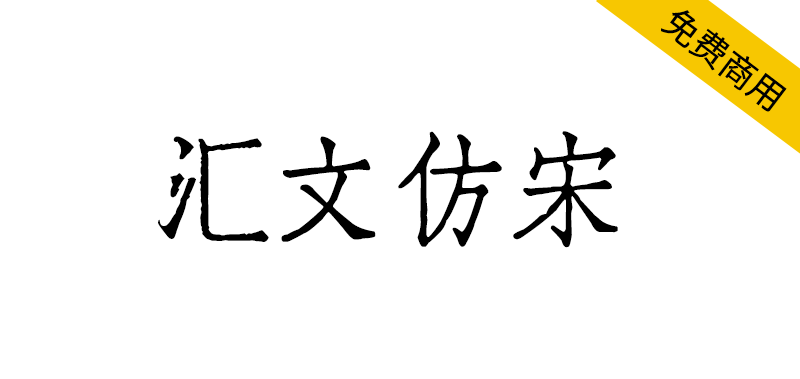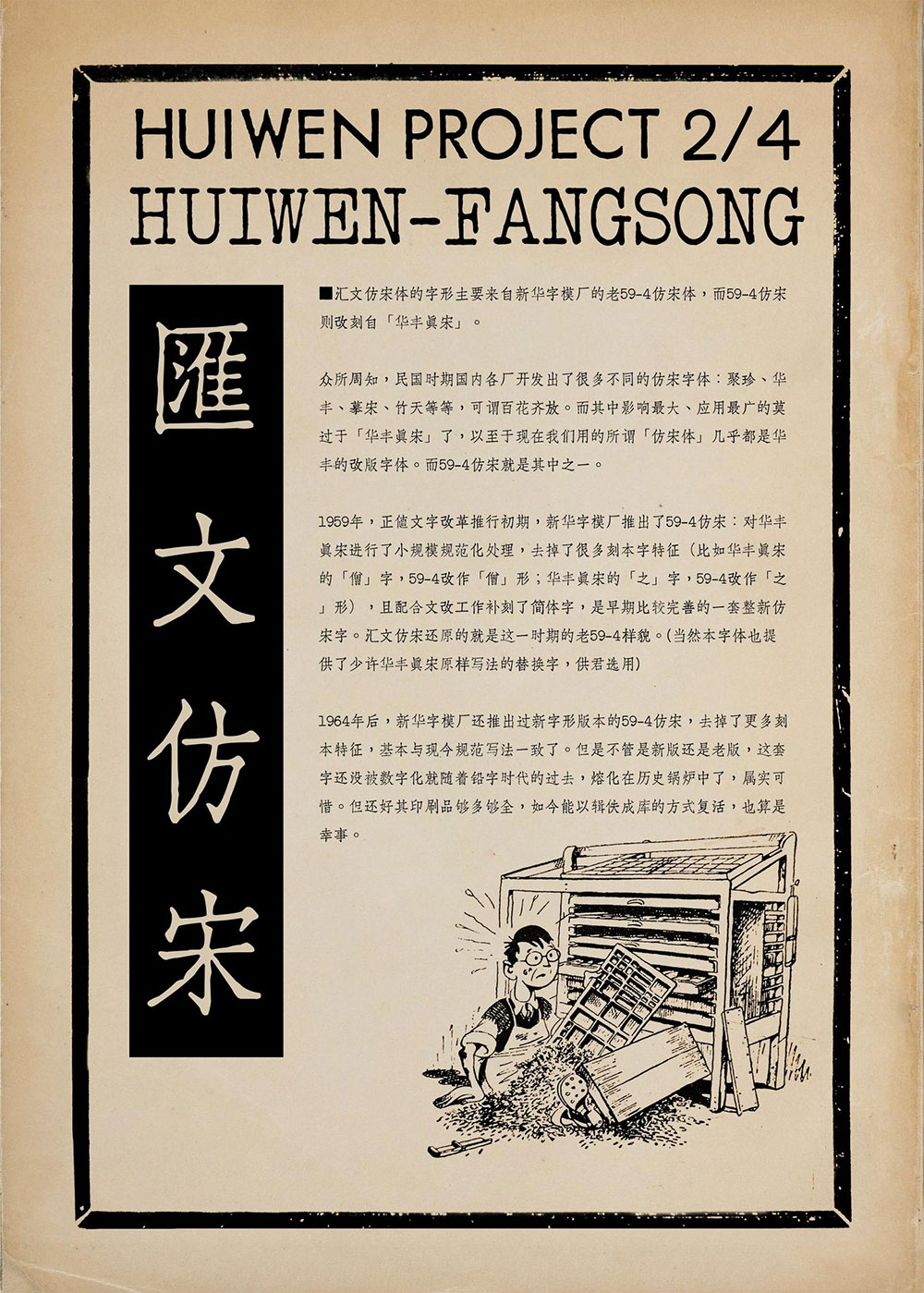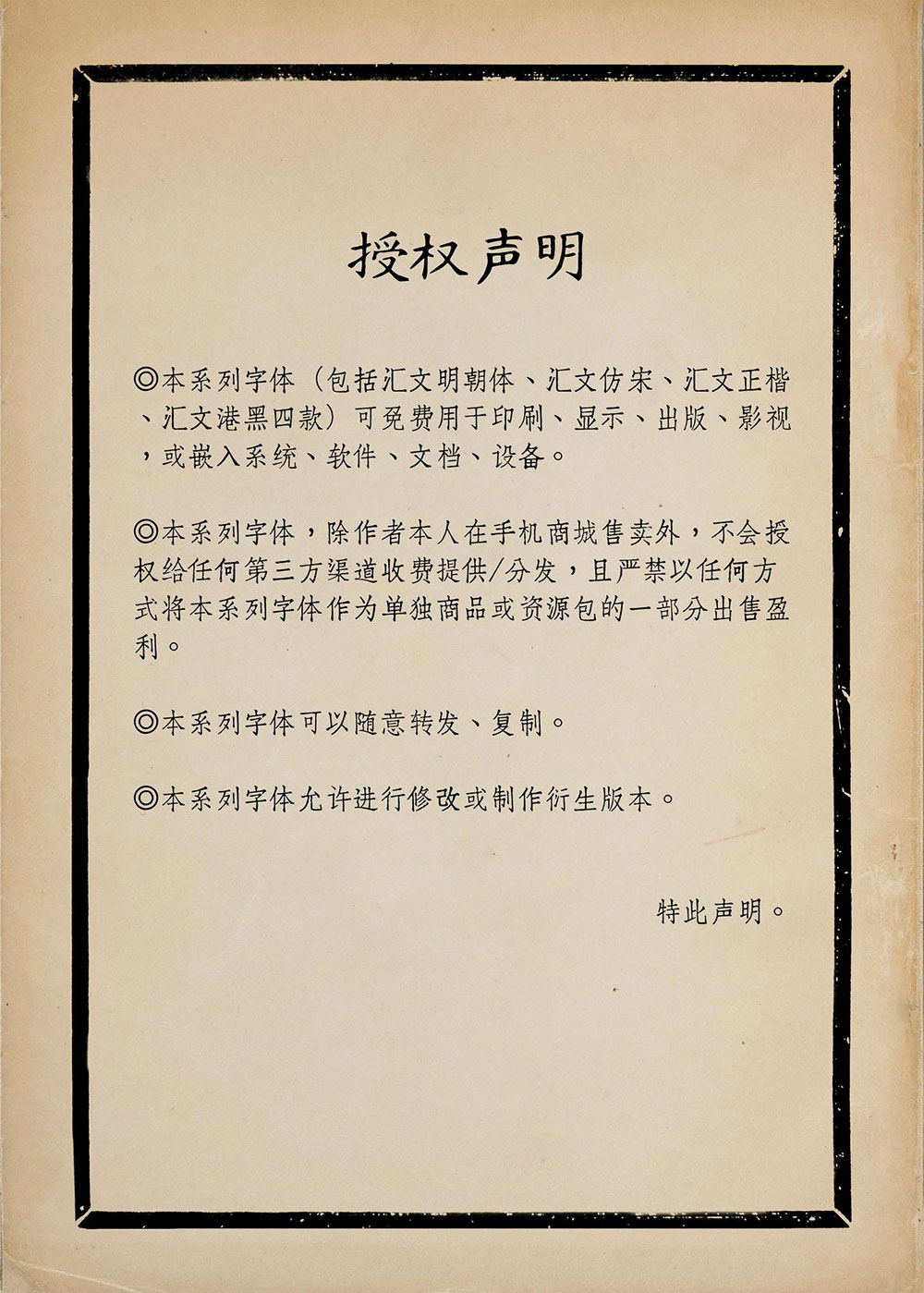
【汇文仿宋】一款复古印刷效果的仿宋字体
你见过铅字时代最美的仿宋字体吗?汇文仿宋体复刻自1959年新华字模厂的老59-4仿宋,其源头正是民国影响最广的「华丰真宋」。它保留了刻本韵味,又融入简体规范,曾随铅字消失于历史,如今却从旧印刷品中被逐字辑佚复活。这款兼具复古美感与实用性的免费字体,究竟还原了多少失落的细节?点击揭晓。
【汇文仿宋】一款复古印刷效果的仿宋字体
汇文仿宋体的字形主要来自新华字模厂的老59-4仿宋体,而59-4仿宋则改刻自「华丰真宋」。众所周知,民国时期国内各厂开发出了很多不同的仿宋字体,聚珍、华丰、摹宋、竹天等等,可谓百花齐放。而其中影响最大、应用最广的莫过于「华丰真宋」了,以至于现在我们用的所谓「仿宋体」几乎都是华丰改版字体。而59-4仿宋就是其中之一。
1959年,真值文字改革推行初期,新华字模厂推出了59-4仿宋:对华丰真宋进行了小规模规范处理,去掉了很多刻本字特征,且配合文改工作补刻了简体字,是早期比较完善的一套整新仿宋字。汇文仿宋还原的就是这一时期的老59-4样貌(当然本字体也提供了少许华丰真宋原样写法的替换字,供君选用)
1964年后,新华字模厂还推出过新字形版本的59-4仿宋,去掉了更多刻本特征,基本与现今规范写法一致了。但是不管新版还是老版,这套字还没被数字化就随着铅字时代的过去,熔化在历史锅炉中了,属实可惜。但还好其印刷品够多够全,如今能以辑佚成库的方式复活,也算是幸事。
【汇文仿宋】一款复古印刷效果的仿宋字体